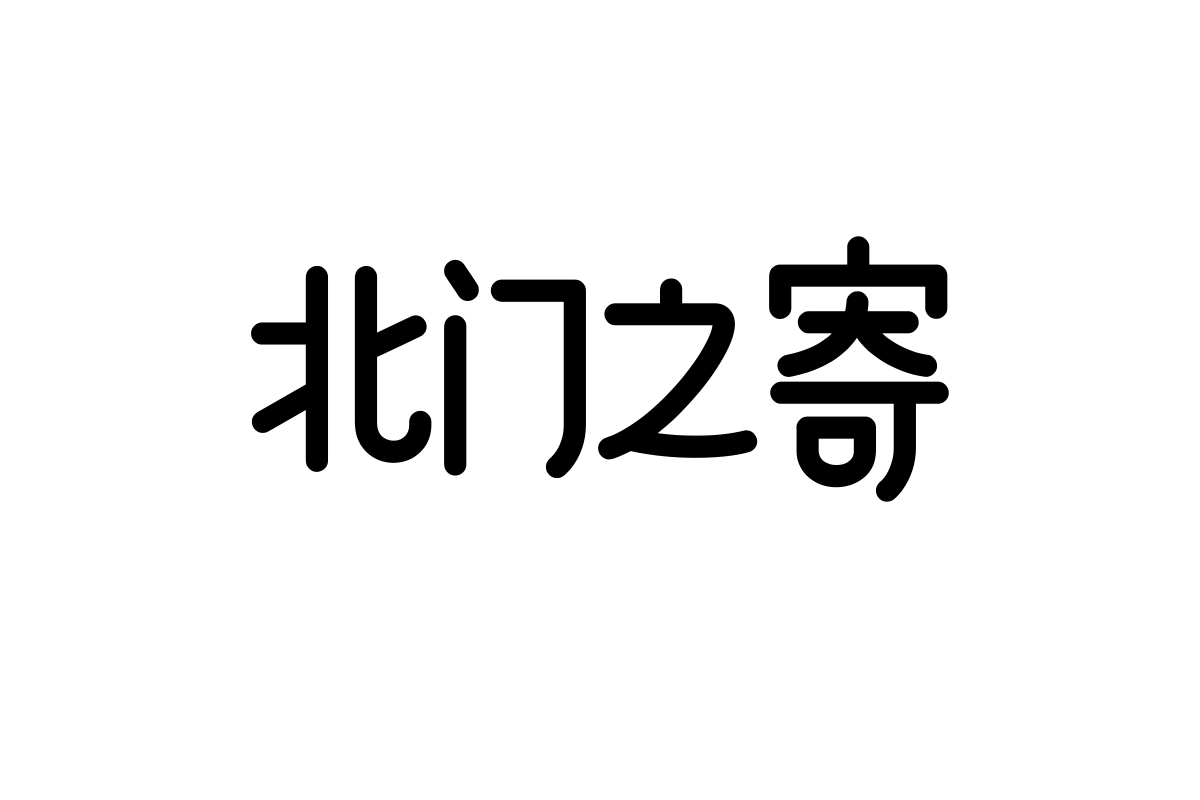
上首童年体是一套专为儿童设计的字体,其特点是字形圆润可爱,笔画流畅自然,适合用于儿童读物、卡通动画等场景。这套字体的特点是:
1. 字形圆润:上首童年体的字形设计圆润饱满,给人一种温馨可爱的感觉。
2. 笔画流畅:字体的笔画线条流畅,没有过多的断点和棱角,使得阅读起来更加舒适。
3. 结构简洁:字体的结构简洁明了,没有过多的装饰性元素,便于识别和记忆。
4. 易读性强:由于字体的笔画简单,且字形圆润,因此阅读起来容易理解,不易产生视觉疲劳。
5. 适用范围广:上首童年体适用于各种儿童读物、卡通动画、儿童游戏等场景,具有较强的通用性。
总之,上首童年体是一款适合儿童使用的可爱字体,其圆润可爱的字形和流畅自然的笔画使得阅读体验更佳。